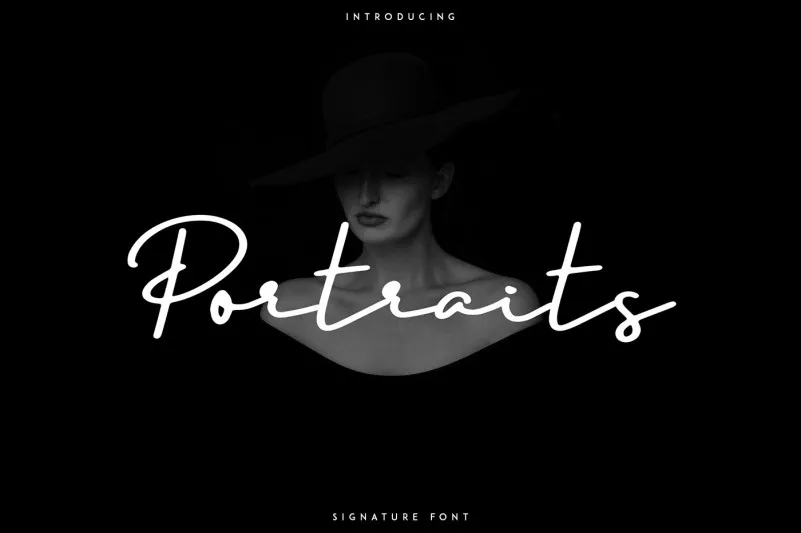
Portraits – Signature Font – Download Grátis
Introduzimos a Portraits Signature font. Esta é uma fonte criada para assinaturas, com um design limpo e multilíngue, oferecendo suporte à várias línguas. A Portraits é altamente versátil e funciona maravilhosamente tanto em grandes como em pequenos tamanhos. Ela se destaca por sua capacidade de expressar personalidades diversas através dos textos mais simples até as mensagens mais elaboradas. Seja para assinaturas, logos ou qualquer aplicação que exija uma fonte limpa e versátil, a Portraits é a escolha certa. Através desta fonte, seu trabalho será ainda mais expressivo e profissional.